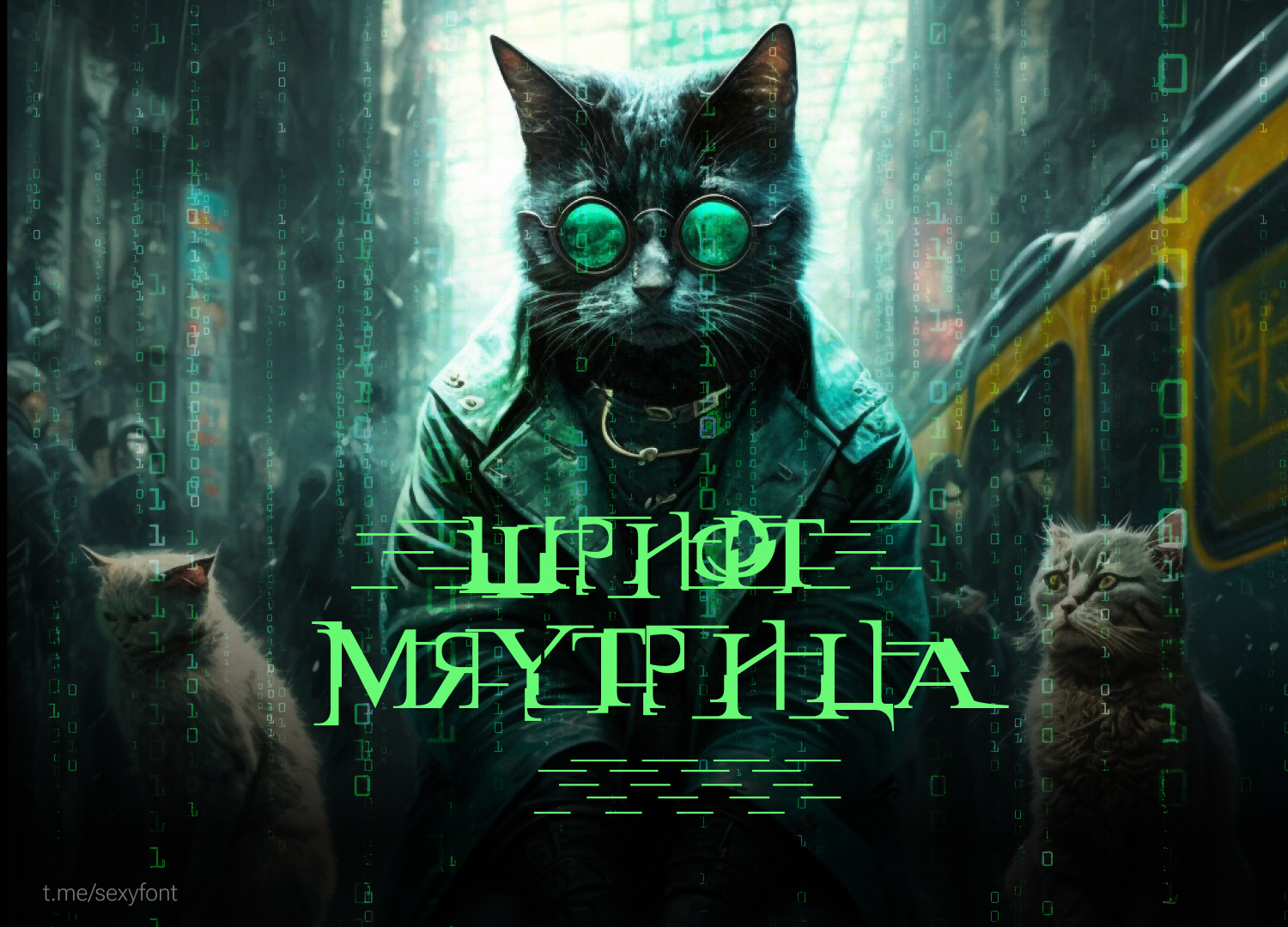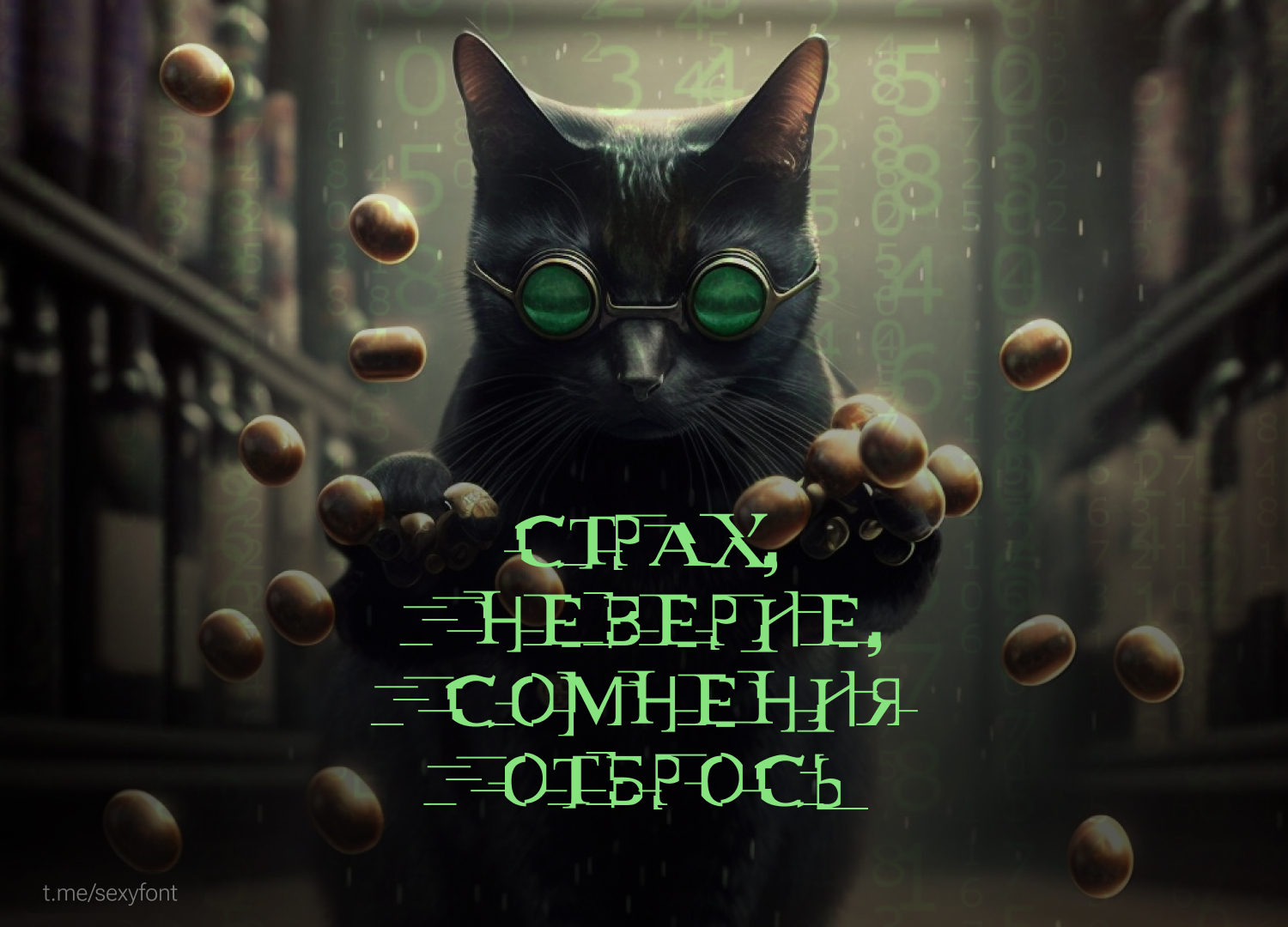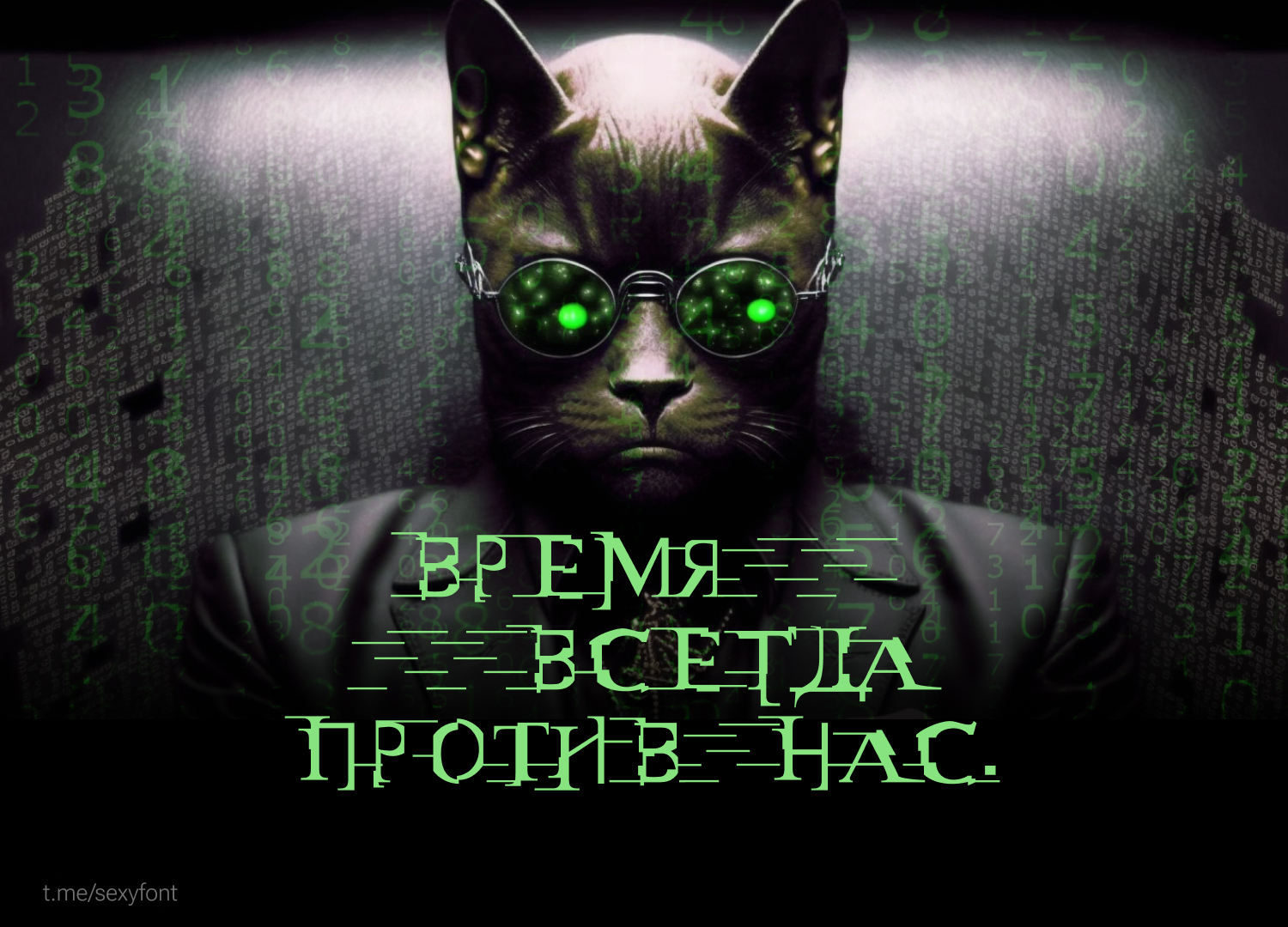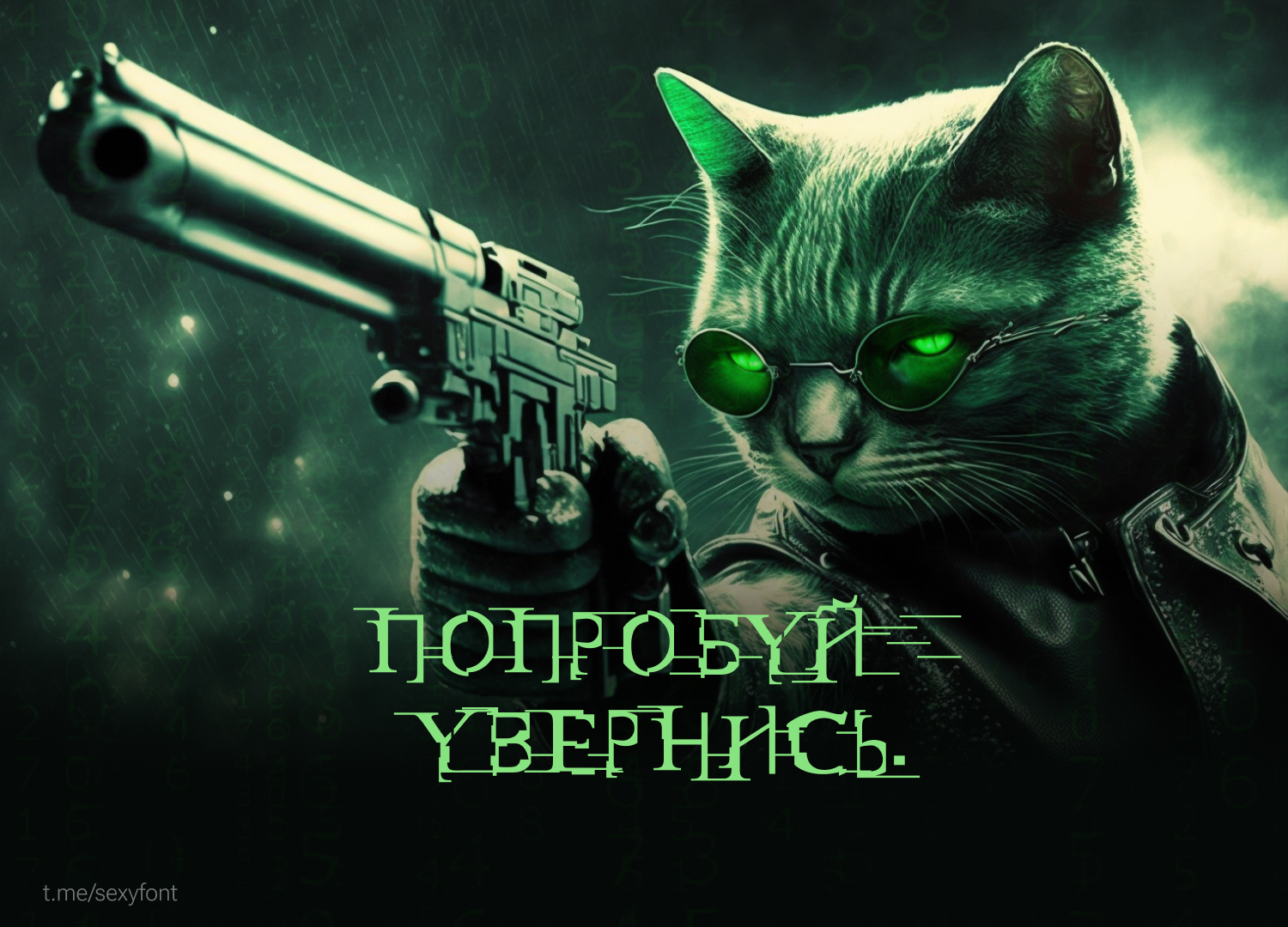
Шрифт из матрицы. Кириллица
Специфичный шрифт из фильма. Использовать лучше в коротких фразах на 2-3 слова. Но как декоративное разнообразие оч даже может подойти. К примеру я создал вот такую альтернативную вариацию Мяутрицы Не нашел лицензии на кириллицу, но на 99% уверен, что бесплатно для всего)